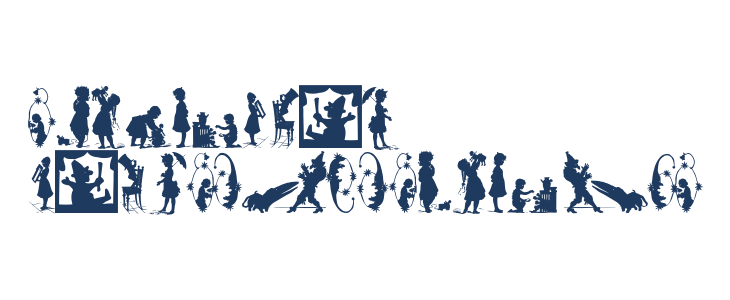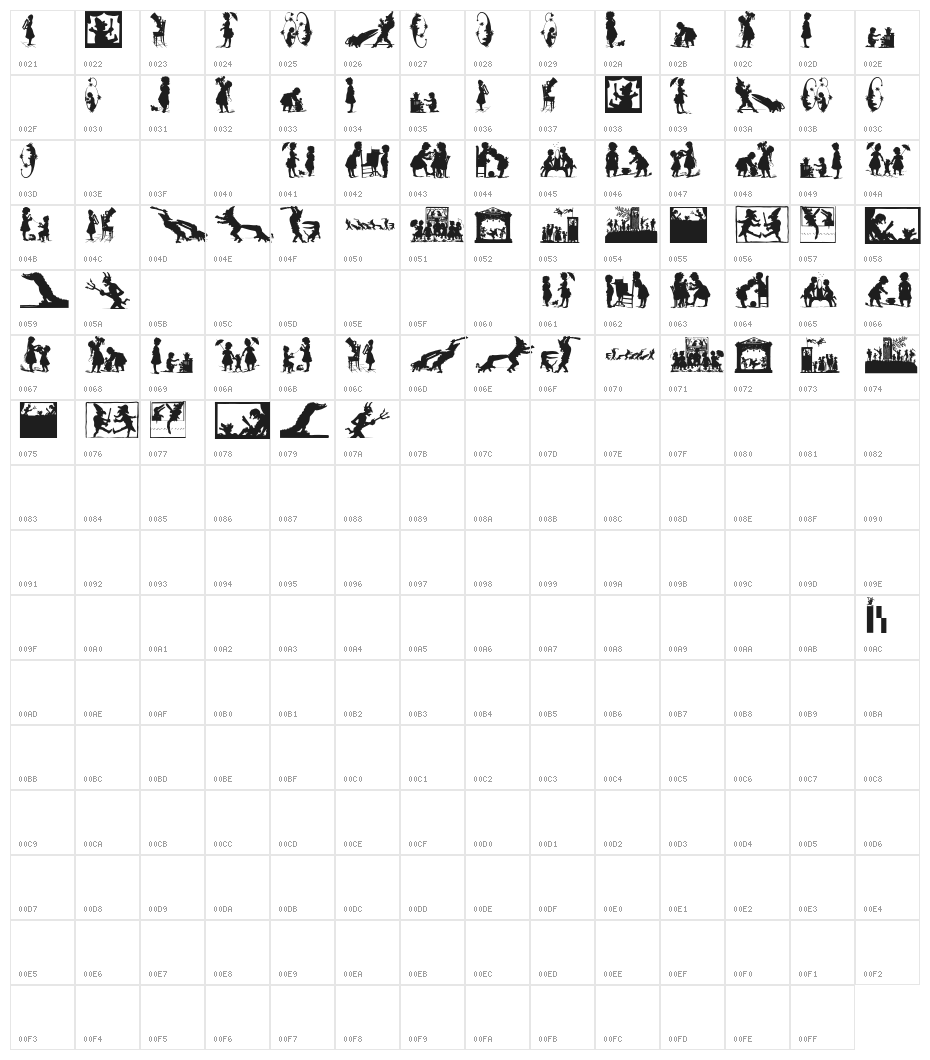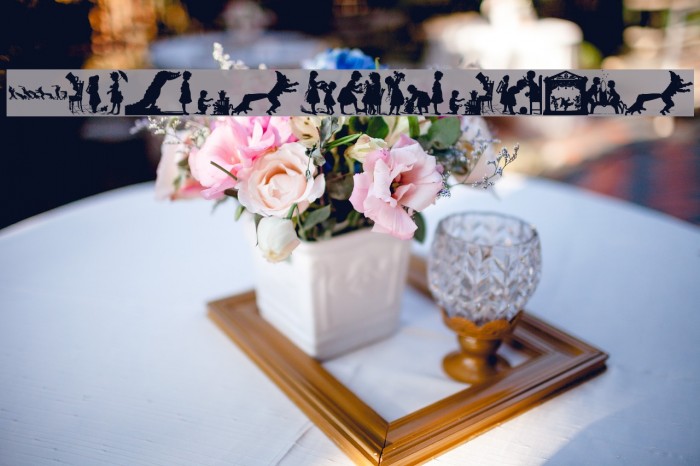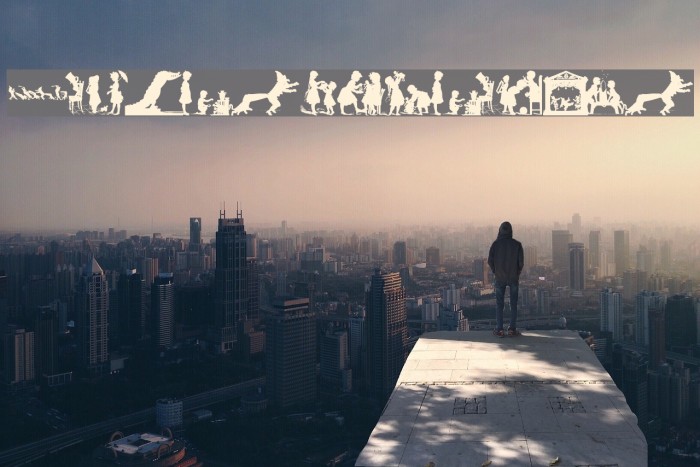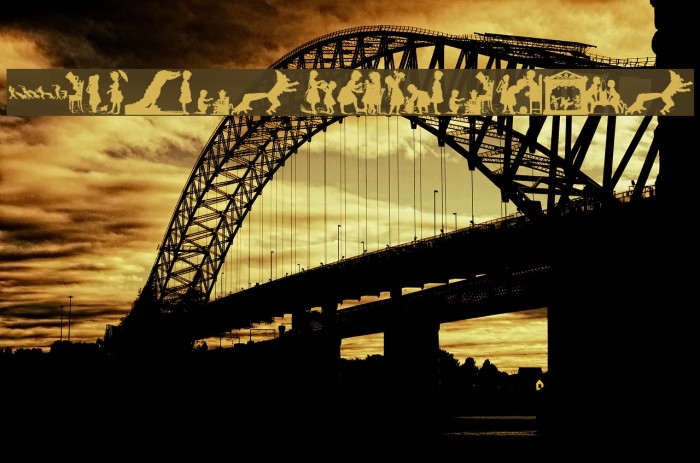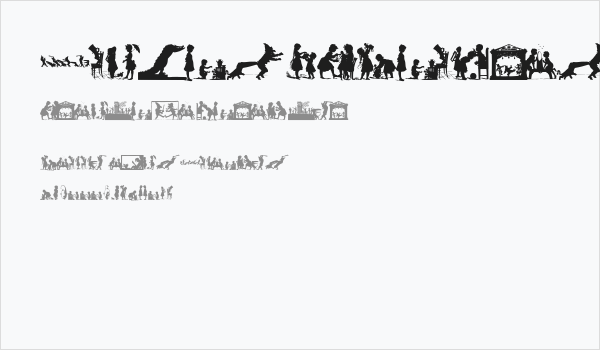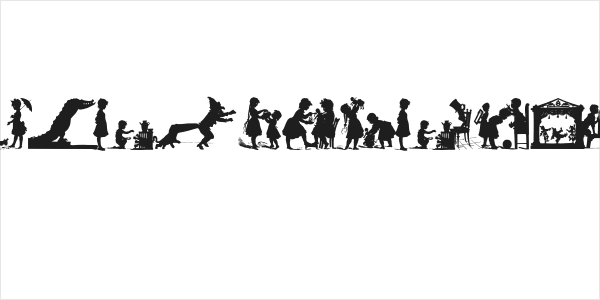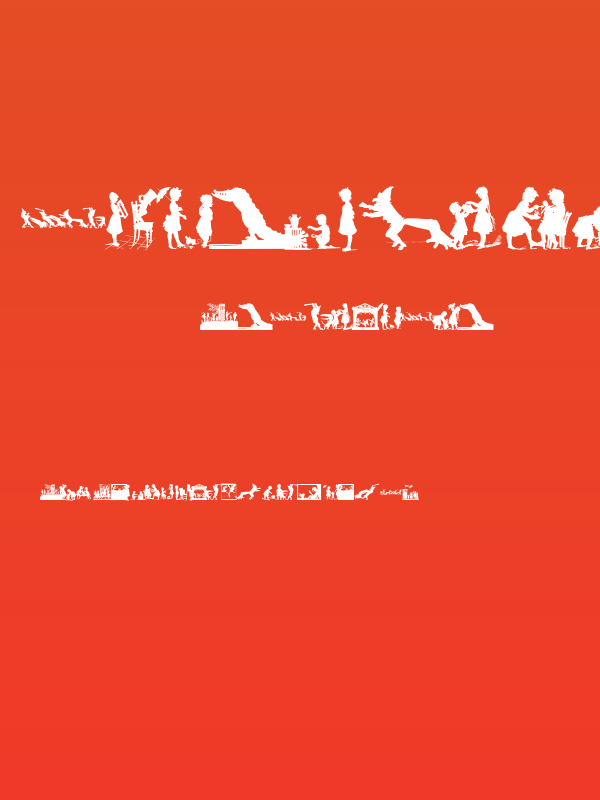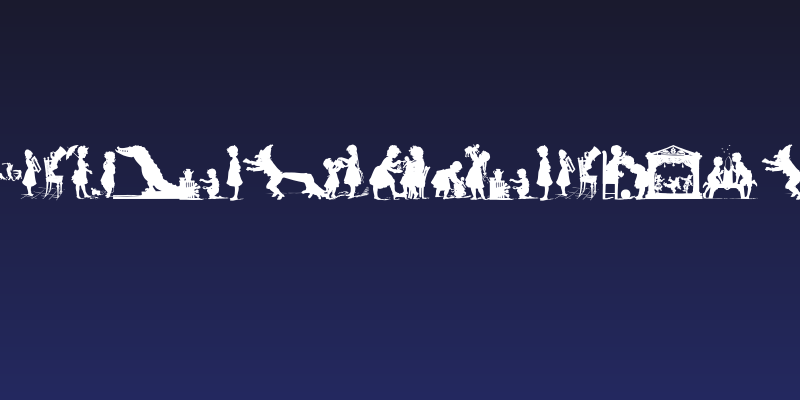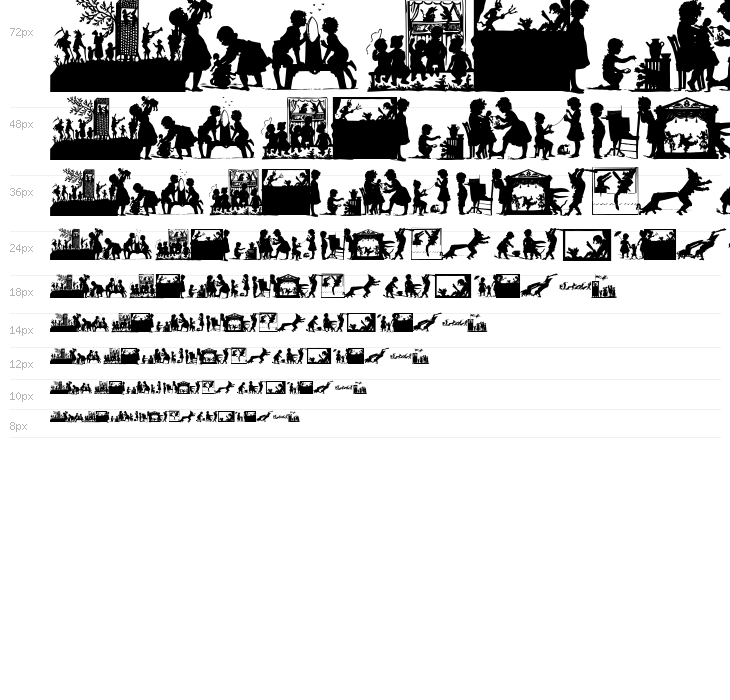
PlayingChildren Font
| 用途 | Logos, Decorative headlines, Artistic projects |
| おすすめプロジェクト | Ideal for children's book covers, playful event invitations, nursery decor, and whimsical branding projects. |